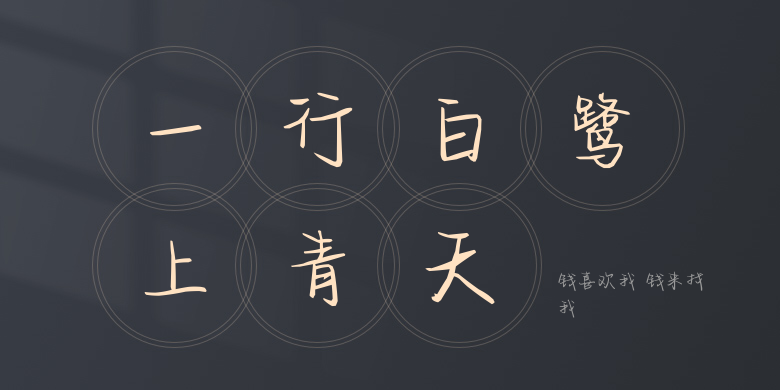
钱喜欢我 钱来找我
钱喜欢我 钱来找我,这款字体结构工整、笔画清晰,兼顾美观与易读性,适用于标题、正文、海报、包装、LOGO 等多种场景。字形优雅稳定,风格百搭耐看,适配日常排版与创意设计,让文字呈现更舒适、更具质感。钱喜欢我 钱来找我一笔一画,皆是细节,以均衡的比例、流畅的线条打造舒适视觉体验,字形端正大气,风格简约现代。无论是商业设计、品牌宣传还是日常排版,都能轻松驾驭,让文字更有格调与力量。钱喜欢我 钱来找我字体下载。